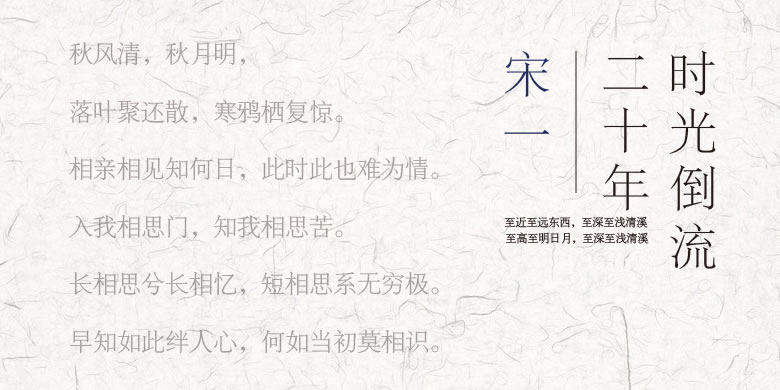
方正宋一又名字典宋,是20世纪60年代初上海印刷技术研究所字体设计室专门为《辞海》正文用字设计的;20世纪90年代方正对其字稿进行了数字化。方正宋一的字面较大,横竖笔画粗细差别不明显,因为通常字典的正文字号较小,较大的字面可以保证文字的清晰度。其次,它的笔画偏细,一方面是为了适应当时的铅字印刷工艺(油墨拓印时会有一定程度的外溢),另一方面是为了满足字典正文排版对文字结构清晰的要求。基于以上特点,不建议将方正宋一用作杂志、书籍的正文字体,但可用于一些小字号的说明性文字。